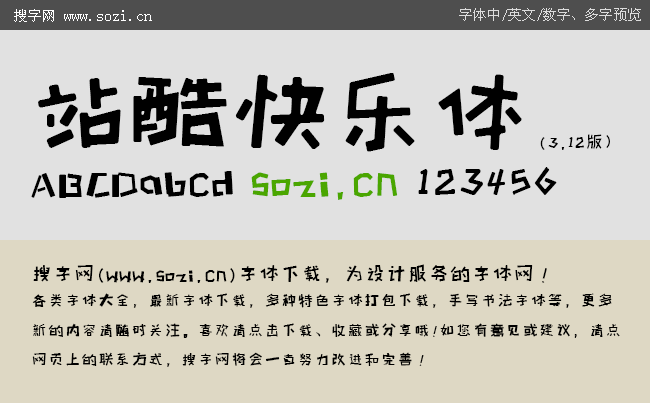
站酷快樂體
搜字網(wǎng)提供一款站酷快樂體中文字體下載,站酷快樂體是一例輕松和簡單風(fēng)格的字體,由150位喜歡字體設(shè)計的字體愛好者制作,供所有人永久免費使用(可商用)的公益字體,筆畫結(jié)構(gòu)靈活,風(fēng)格輕松活潑,適用于網(wǎng)頁廣告、海報設(shè)計,圖書印刷等廣告設(shè)計場合使用。